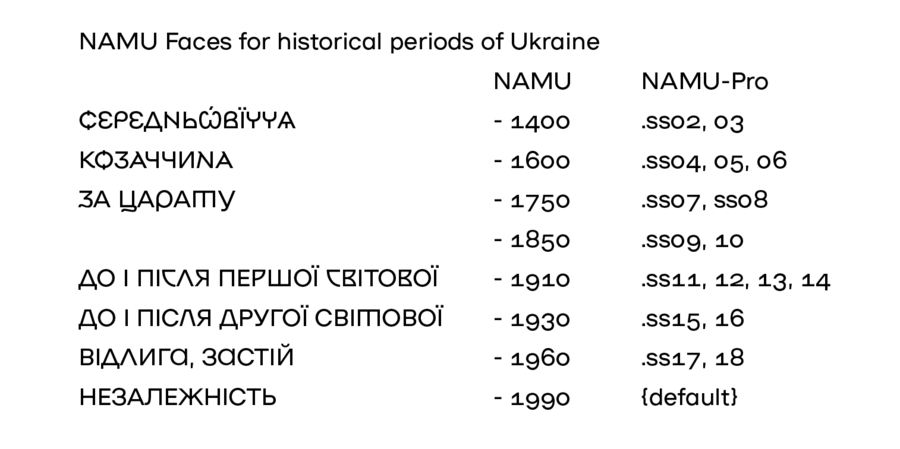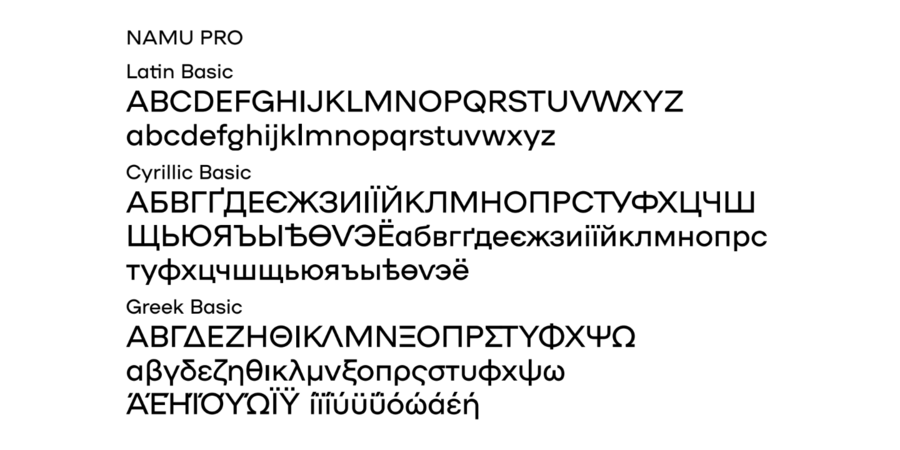
NAMU Pro – повна професійна версія безкоштовної гарнітури для Національного художнього музею України. NAMU – геометричний гротеск зі смаколиками, херітажем, челенджьом та таймлайном. Переможець Red Dot 2019 у категорії «Корпоративний дизайн та айдентика». Наприкінці 2018 року Національний художній музей України та Banda презентували нову айдентику. Шрифт NAMU став основою візуального стилю. Для створення шрифту дизайнер Дмитро Растворцев з головою занурився у дослідження музейного фонду, архівних документів і накреслень стародавніх літер. У результаті фінальний шрифт NAMU має 20 стилістичних наборів у версії NAMU Pro та 9 окремих накреслень для кожного історичного періоду. Усі шрифти NAMU є безкоштовними для комерційного та некомерційного використання. Але файли шрифтів не можна декомпілювати. Ліцензія Creative Commons CC BY-ND 4.0. Шрифт розробив Дмитро Растворцев у 2018-2022 роках.
Асоціації з сімейством шрифтів NAMU ProОсобистість і характер гарнітури:
урбаністичний, зрозумілий, технічний, формальний, елементарний, мінімалістичний, точний, рівний, стабільний, статичний, Простий, нейтральний, логічний, прагматичний, практичний, твердий, лаконічний, доступний, серйозний, надійний, впевнений, стійкий, автоматичний, штучний, холодний, машинний, інженерний, міський, чіткий, гострий, креслярський, чистий, сучасний, модний, самостійний, архітектурний
хімія, математика, урбаністика, техніка, прилад, код, креслення, конструктор, інженер, автоматика, Місто, наука, дизайн, архітектура, коворкінг, меблі, мода, технології, інновації, девайс, гаджет, банкнота, монета, вода, небо Гарнітура має ознаки стилів: